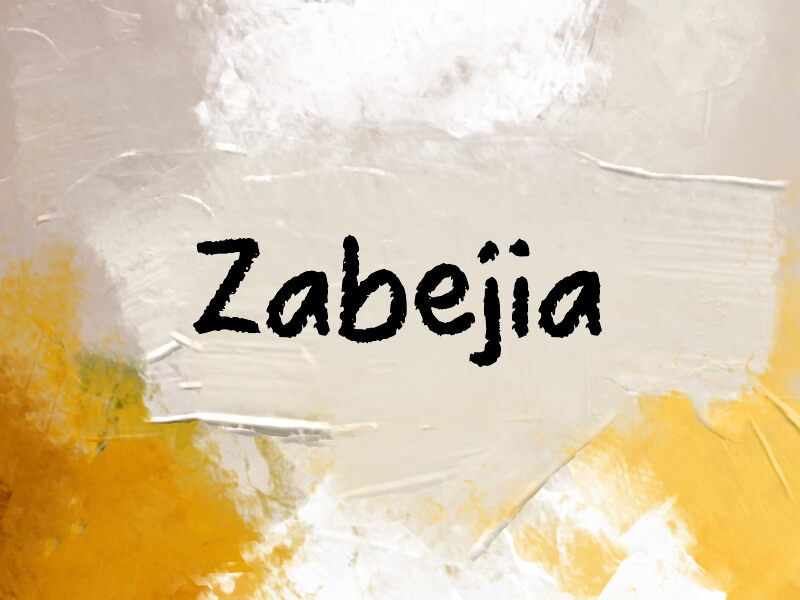
Zabejia
Zabejia, bezplatný font typu brush od Wep, využíva textúru suchého atramentu a rázne, ručne maľované kontúry, ktoré dodávajú písmenám ošľahaný a zvetraný vzhľad. Nerovnomerný povrch je v celom súbore znakov konzistentný, takže písmo nepôsobí ako uhladený rukopis, ale skôr ako rýchle ťahy štetcom, zachytené v momente, kým boli ešte surové.
Táto surová textúra sa výborne hodí na plagáty, hudobné vizuály, streetwearovú grafiku, kaviarne a obaly, ktoré si vyžadujú priamy, ručne vyrobený nádych. Najlepšie vynikne v krátkych nadpisoch a logách, kde zlomené hrany a kompaktný rytmus dodávajú pár slovám potrebnú drsnosť, aby vynikli v každom dizajne.